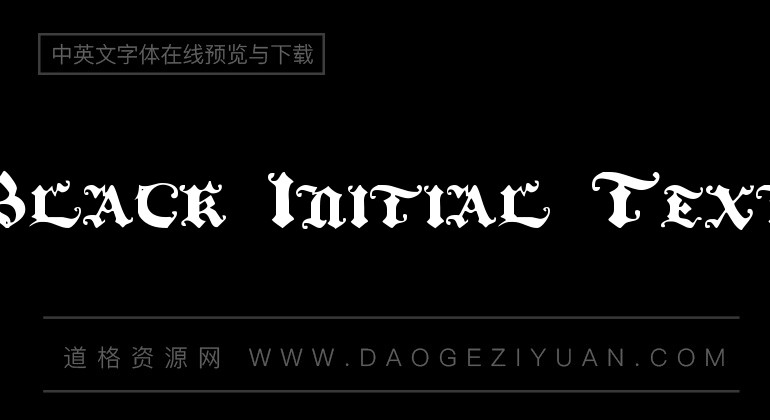
Black Initial Text 是一种装饰性的字体,它的特点是字体笔画厚重,有着明显的装饰效果和艺术感。这种字体的设计灵感来自于英国中世纪和文艺复兴时期的书法艺术,它的整体风格非常传统、古典,常被用于书籍封面、广告海报、宣传画等设计之中。 Black Initial Text 字体有着非常醒目的外形,它的笔画粗细不均,有时甚至会出现一些小花纹和图案。这使得它看起来非常有趣,同时也赋予了它一定的艺术价值。不过,由于这种字体的装饰性比较强,所以在实际应用中需要格外注意字体大小和线条粗细的搭配,以免影响阅读效果。 总的来说,Black Initial Text 字体是一种非常具有装饰性和艺术感的字体,非常适合用于需要突出文本主题或者强调设计感的场合。内容介绍
Black Initial Text是一款非常不错的手写艺术字体,具有很好的视觉感,适合于文化类的宣传设计、商业类品牌的广告和产品包装设计以及个性化文字排版等较多场景。